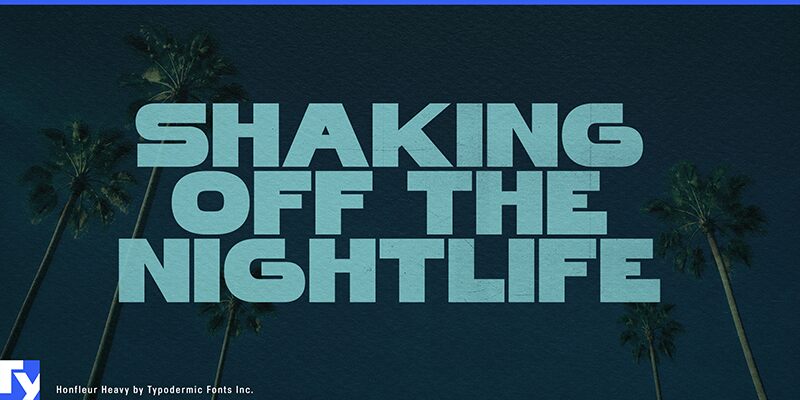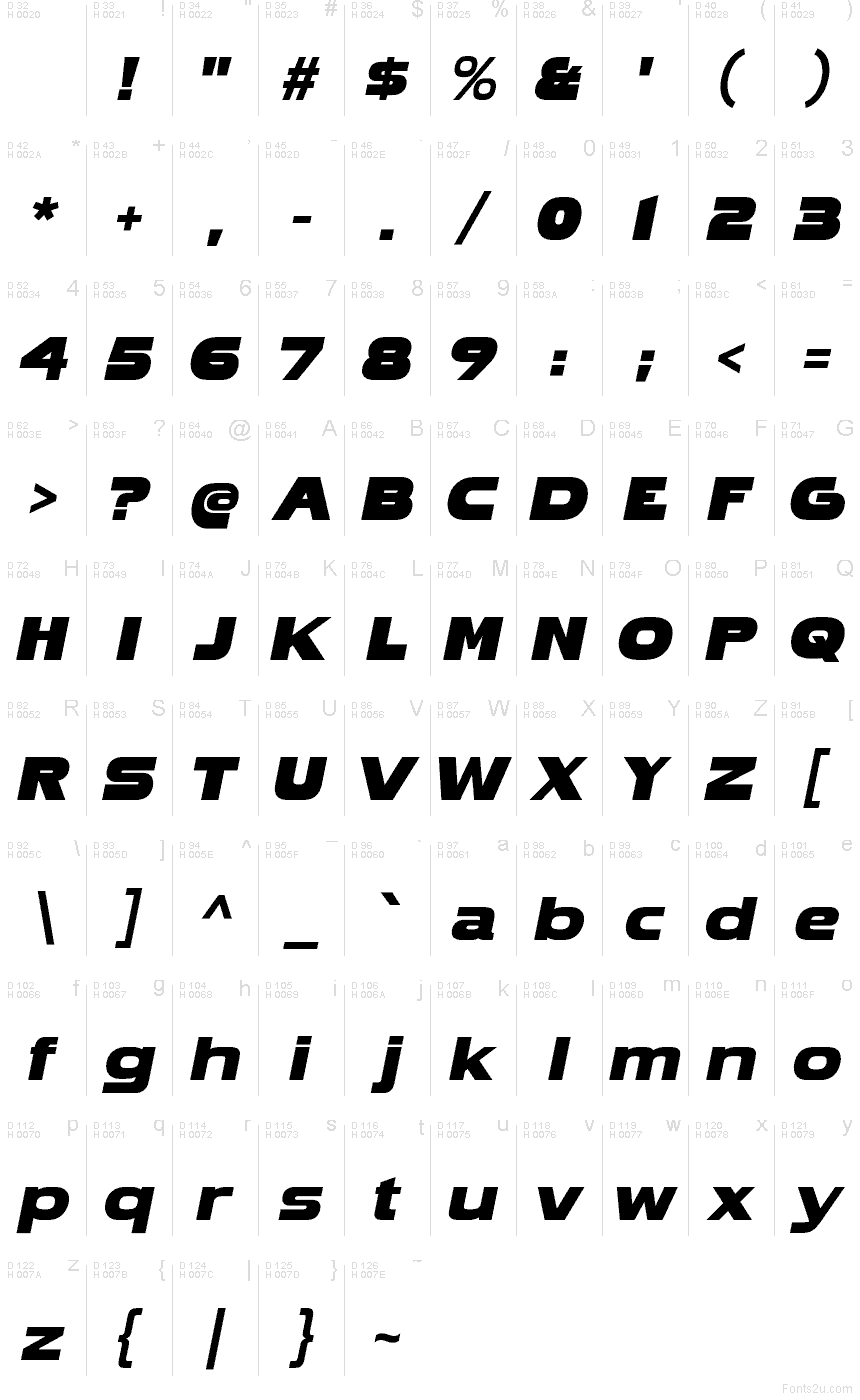
Honfleur Heavy Italic de Typodermic Fonts Inc. est une police d'affichage rétro gratuite, dotée d'une inclinaison dynamique et de caractères arrondis et épais. Ses traits larges et ses coins adoucis rappellent les enseignes et le sportswear de la fin du XXe siècle, tandis que son mouvement compact vers l'avant lui donne un aspect percutant plutôt que purement nostalgique.
Elle convient parfaitement aux titres d'affiches, au packaging, aux logos, aux unes de magazines et aux cartons de titres nécessitant de la vitesse et du caractère. Grâce à son épaisseur généreuse et à ses courbes fluides, c'est aussi un excellent choix pour les phrases de branding courtes ou les monogrammes, car l'élan de l'italique dynamise même les mots les plus courts.